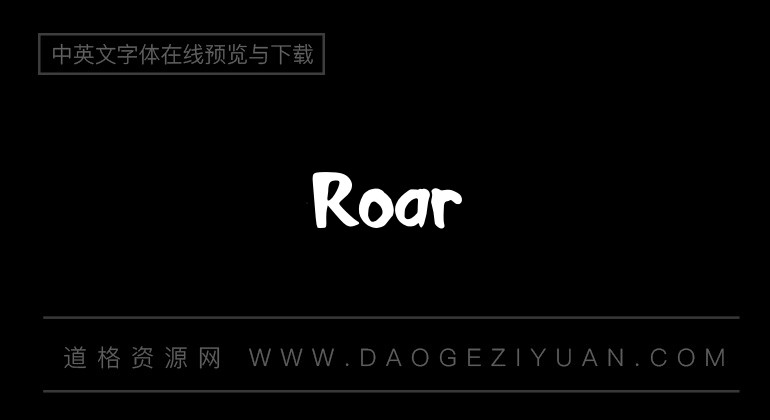
Roar 字体是一款来自 Fontfabric 的新字体,它拥有现代风格的外观,具有清晰的线条和细节,可以用于创建多种多样的设计,包括海报、标题、标签、广告等等。Roar 字体的特点是它的字母形状经过精心设计,使它们更具有现代感,并且有许多替代字体可供选择,使用者可以根据自己的需要调整字体的大小和风格。内容介绍
Roar是一款非常不错的手写艺术字体,具有很好的视觉感,适合于文化类的宣传设计、商业类品牌的广告和产品包装设计以及个性化文字排版等较多场景。